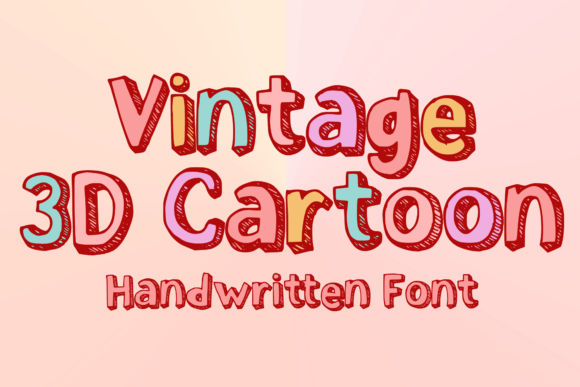
Vintage 3d Cartoon
Visão Geral da Fonte Vintage 3D Cartoon
A Vintage 3D Cartoon é uma fonte hand‑lettering com efeito tridimensional que traz um ar descontraído e alegre a qualquer projeto. Seu estilo “cartoon” combina linhas suaves, contornos leves e sombras sutis, criando a sensação de profundidade sem perder a legibilidade. Perfeita para quem busca um toque casual e ao mesmo tempo profissional.
- Design 3D autêntico: sombras internas e externas que dão volume ao texto.
- Estilo manuscrito: traços irregulares que lembram escrita à mão, ideal para projetos infantis.
- Versatilidade: funciona bem em camisetas, livros infantis, cartões, adesivos, pôsteres e muito mais.
Para Que Tipo de Projeto É Indicada?
Se você está desenvolvendo designs que precisam de um toque casual, a Vintage 3D Cartoon se destaca nas seguintes aplicações:
- Camisetas e merchandise para público jovem.
- Ilustrações de livros e revistas infantis.
- Cartões de felicitações, convites de aniversário e lembrancinhas.
- Adesivos, stickers e etiquetas decorativas.
- Pôsteres promocionais, flyers e banners de eventos divertidos.
Prós e Contras
- Pró: muito fácil de ler mesmo em tamanhos pequenos.
- Pró: dá um aspecto “hand‑drawn” sem perder o profissionalismo.
- Contra: pode não ser adequada para projetos extremamente formais ou corporativos.
- Contra: requer atenção ao contraste de cor para garantir a visibilidade da sombra 3D.
Dicas de Uso para Maximizar o Impacto
- Combine a Vintage 3D Cartoon com cores vibrantes (amarelo, rosa, azul) para realçar o efeito tridimensional.
- Use fundos claros ou texturizados que permitam a sombra da fonte “respirar”.
- Para impressão em camisetas, prefira cores de tinta que contrastem bem com a sombra interna.
- Emparelhe com fontes sans‑serif simples (por exemplo, Montserrat ou Open Sans) para equilibrar o visual.
A Vintage 3D Cartoon conquista quem busca uma tipografia divertida, versátil e pronta para ser aplicada em múltiplos formatos. Seja para criar camisetas criativas, ilustrar livros infantis ou dar vida a cartões de felicitações, essa fonte entrega um visual moderno com um toque nostálgico de “desenho animado”. Experimente hoje mesmo e descubra como ela pode transformar seus projetos em verdadeiras obras‑de‑arte lúdicas!